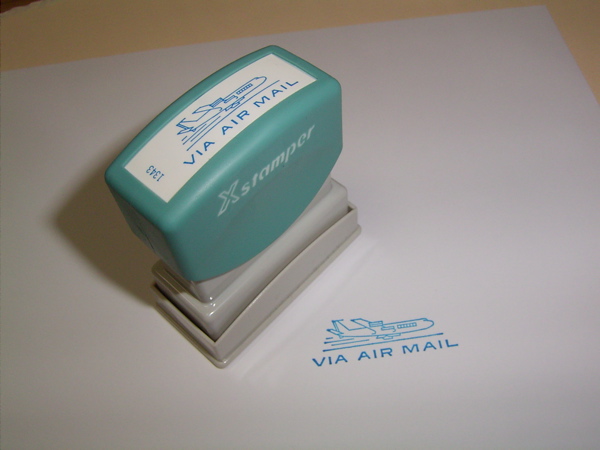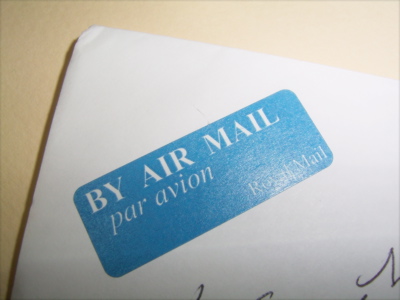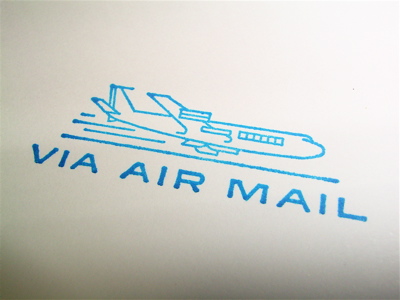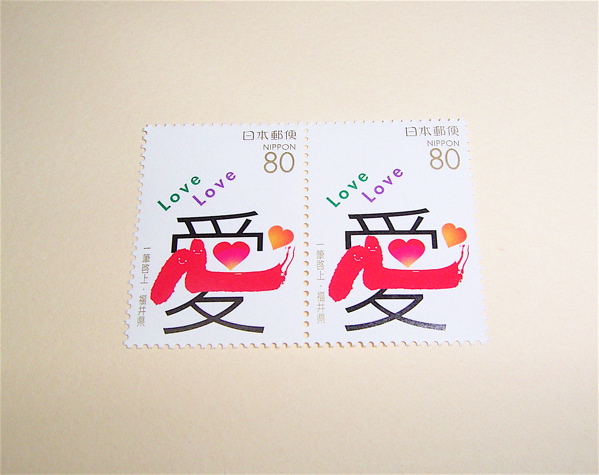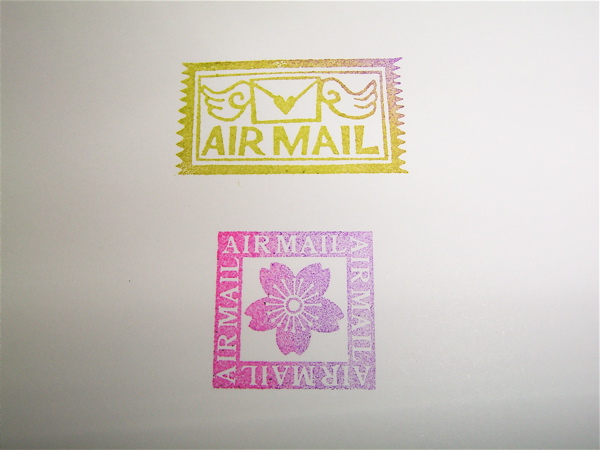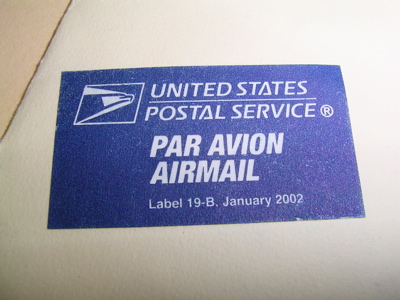
ルーリングペンWS in 神戸 1
週末の土、日は、神戸カリグラフィーフォーラム(KCF)主催の
WSをしてまいりました。
ツールは、ルーリングペンです。あのゴッチャンのではなく、
フツーの烏口を使います。
総勢20名・・・ゼーゼー・・・普段のクラスは6名なのに、3倍以上の
お客様でございます。皆様烏口とお友達になるのは初めての方も多く、「ルーリングペンと仲良くなる」をテーマに進めてまいりました。
烏口のご本業はとにかく「おいらぁ、人生まっすぐさぁ〜」というぐらい、一本気な、否、一本線を
引くことにあります。円を描くにはそれ様のがあるようですし・・・。なので、もちろん曲線には滅法弱いざんす。なので、最初はなだめる様にサンドペーパーで気持ち丸くなって頂きます。
本当に軽〜〜く、軽〜〜く!空気の皮一枚ほど挟んでの作業でございます。(WSのときは、この言葉が出なかった・・・くぅ〜)
上の画像・・・変なサンプルでしょう〜!これは、ルーリングペンの先っちょと腹(横の部分)を使う練習なんです。
これがルーリングペンと仲良くなる基本のように思います。ルーリングペンは固いのであります。
だから、クイルやブロードエッジのように圧を加えればすぐに程よい太さが出るというのではありません!それにみんな手の癖、筆圧・・・様々です。とにかく、先っちょ!腹っちょ!と手がその感覚を覚えていかなくてはなりません。
うはは〜!生徒さん達は、あっという間に想像力豊かな世界を描きながら先っちょ!腹っちょの練習をこなしていきます。
線を描きながらコンポジションも行っていく時、参考にしたのが、アフリカの原住民が作り出す布地でした。
とても幾何学的だったのです。一番上の画像で下側の紙の付箋がついてるのが、
その布地を参考にしたもの。アフリカっていう言葉が頭にあったお嬢さんは、もうアフリカが止まらなかったようで〜キャハハ!シマウマに、ライオンに、ペンギンまで〜。そうかそういう展開もあったかと微笑ましくなりました。楽しみながら慣れるのが一番ですもの!
最初通りかかったときは、途中で
苦戦してるのかしら?と心配でしたが、そんなことはご無用〜!でした。次に見に行ったら、ワォ〜!
いつのまにか凄いことになってます!空間の処理が素敵で、見入ってしまいました!
これも練習のバリエーションで、イニシャルをたくさん作っていくのです。こういう時は、とにかく最初にモノライン(先っちょ)で右方向へ一列にバンバンと少しずつ変化させながら案を出します。
その後は下方向へ腹っちょを使いながら表情を変えていきます。
こうすれば、イニシャルのバリエーションなどあっという間に何十個も出来ちゃいますから〜!!・・・ん?最後の方は、突然変異か・・・?
レイアウト用紙にばかりではつまらないので、キャンソン・ミ・タントのようなラフな色紙に白で書いてみます。
所々にイニシャルデザインも
置きながら練習していき、
どこかに色鉛筆で色をつけて
いっても可愛いです。
練習をしたら、必ず、小作品の
ようなものを作ると励みになりますね。「こんな練習をしていてどうなるの〜」と不安なお嬢さん!
作りましょう〜!
ほら!こうやってレイアウトしながら、線を書き書き・・・。
こんな所にイニシャルをポン!
最後に文章をのせてみてもいいですねぇ〜。
色をつければ、出来上がり!
白く書くには、水彩紙は使用しないので、色鉛筆が
便利です。木炭紙なんかだと相性良いですし!
こんなminimumも練習しましたね。
これも先っちょ、腹っちょの練習で、しかも連続する動きの練習です。
横ばっかりじゃなくてもいいんです!たまには縦にも書きましょう〜。太い線を書くには、ペンは紙面に近くないと出ません。おのずと持ち方に限界が出てくることが理解できます。ルーリングペンは、持ち方も一つではないのです。
でもminimumばかりで・・・この先は?
もちろん!作りましょう〜。
ミニ作品(もどき)で良いのです。
この黒い紙のは、全てminimumだけで構成されています。
いろんなminimumがあるぞ〜!!
こういう練習をたくさんして、
いずれは曲線中心のカーシブへと
発展していくことでしょう〜!
カーシブになると、圧をかける部分が難しいです。
この小作品たちは、minimumも含めて、全て同じルーリングペンで書いています。
先っちょ!腹っちょ!の操作を覚えると同じペンで細い線から太い線まで書けるのです。
さ〜て、次回は20人の妄想カリ人達爆発!?
怒涛のカード作りまでをご紹介致します〜!!みんな凄いんだぁ〜!
彼女のパレット
mojitor-sさんのワークショップ楽しそうですね!素敵な色が勢ぞろいでうっとりしました。
綴じ糸にマルッコちゃんつけるの、いいでしょ?ドットにぴったりですね。
さて、先日のこと。
「sさんのパレットが欲しいわ〜」と言いながら、ブックのページ作りの作業をするためにご自分のパレットを取り出したKyokoさんです。
おやおや、なーに?透明なフタに番号がふってある仕切りのついたパレットです。深さがありますね。
伺ってみると、透明水彩絵の具にご自分で番号をつけ、その番号に対応させたオリジナルのパレット。筆に水をふくませたら、すぐ始められます。
なるほど〜、これはどの色を出したんだっけ?とすぐ忘れてしまいますもんね。
簡単なように見えて、これは優れものです。このケース、実は薬入れなのだそうですよ。7日×4週間で1か月分の薬を入れられるもの。
一つ一つにフタ(錠剤が落ちないように、でしょうか)がついていたそうですが、それをカットしています。
この薬入れのアイディアはもとはお友達から伝授されたそうですが
絵の具に番号をつけたところがKyokoさんオリジナルですね。
こういう薬を入れるケースは、1週間用とか2週間用はよくあるそうなのですが、このような1か月分を入れられるたくさん仕切りのあるタイプは、あちこち探しても見当たらないとか。
彼女とワークショップなどで同じテーブルになった人はわかると思いますが、
とにかく作業が手早いのです。それにはこういう日頃の準備もあったのですねえ。
見習わなきゃ!
と、見ている間にさっさと作業を始めちゃったんですね〜。
少しずつ色を混ぜながら、美しい色が筆からあふれてきたのでした。
ドットそしてまたドット
ドット、ドットのワークショップが終わりました。まるで草間弥生の様。ドットばかりの一日でした。
この色とこの色を合わせると、あらま、こんな色が〜!!
思ってもみない色が出現して、大発見もありますね。
所狭しとパレットが広げられ、頭を整理しながら、格闘しました。
これが本当にひと苦労。色味や鮮やかさに惑わされると、わからなくなってしまいます。
一見明るく見えても、実は以外と暗かったり。ふ〜〜む、難しい。
それをノートに仕立てたページに貼って出来上がり。
一日が終わる夕方には、皆疲労困憊。今日はお昼休みが10分しかなかった〜という方もいて、そうでしょそうでしょ、お疲れですよね。
本当にご苦労さまでした。まだ出来上がっていない人もいたのでこれで全部ではありませんが、それぞれ苦労のかいがあって、とても素晴らしいサンプルブックが出来ました。
今回、本当に疲れちゃったと思いますが、基本色に白黒グレーだけじゃなくて、適当な色を混ぜて仲良しこよしの色をたくさん作ってみましょうね!!
優しさに包まれたなら〜。
私が物欲しそう〜〜〜(かなり)に、mojitor-sさんの
紹介していたペットボトルカバーについて語っていた
ところ・・・カタコン・・・。
ぉお〜幸せの音が・・・カタコン。
その前に・・・バリッバリッ・・・封筒のテープをはがし・・・。
な、な、なんだ!もしかしたら包み紙が・・・手書き?
sさんが洋服を買うあのお店?の包み紙・・・かどうかは
わかりませんが、あのクシュクシュする柔かい紙に
このレイアウト!色鉛筆でビルトアップなカラフルな文字が
いますよ!いますよ!
キャホホ。
こんな贅沢なことでいいのでしょうか?!
そして中身はもちろんあのあったかになるために で
登場したカバーですぅ〜。
ウフフ。ウフフ。
優しさに包まれた気持ちってこういうのを言うんでしょうね。
「ご、ご主人さま・・・。私、とてもヌクヌクでございます。
優しい気持ちとは、このようにフワフワになるので
ございますね・・・。」
ポッチンや、それはペットカバーじゃなくて、
ボトルのカバーざんす!
バックダンサー付き製本はいかが?
週末は、神戸でルーリングペンのWSをしました。寒い中、大勢の方に参加して頂き、
20名の妄想カリ人(勝手にすみません)のすごい発想力に、私も大変刺激を受けた
次第です。WSの様子はまた後日にご紹介いたしますね。ウフフ。
If'n Books demonstration video
WSは受ける方、与える方と、どちらの立場にいても思うことが、「動き」です。
何かをしようとしていて、よく解らなくてどうしようもない時ってありますよね・・・。
(だいたいいつもか・・・)
本の写真を見てわかるときもありますが、実際のところを見られたらどんなに良いだろうか・・・。
今や、動画の時代!探せばあるもんです!
You Tubeで製本についてもたくさん動画があるようです。アクセス数が多い人気のものが
上の画像です。
ちゃんと製本している後でたくさんのダンサーが踊る・・・躍る・・・?「何で?」
クレジットには「her dancers」とかなってますよ・・・!「へっ?」
それは彼女のお友達、ファン、親衛隊なのか・・・それとも彼女の頭の中の人達が
躍ってくれるのか・・・!「ほぉ〜?」
どちらにせよ、製本中の道具は必見!綴じ台が欲しい〜!糊の後にローラーみたいの
かけてるし・・・。
でもついついダンサーに見とれて・・・気付いたら製本終了してます(爆笑)!
動画は助け舟の一つ!それでもWSやクラスに参加するのは、やっぱり「聞いて!」
コミュニケーションが一番大切なんだと思うわけです。
こんなところでお役立ち
今日はワタクシ、お歌の発表会でございます。
久しぶりにミシンを出して衣装(?)のロングスカートも縫いました。学芸会の準備みたいです。
Par Avion
いつも海外へ手紙を出すときは、この航空便用のシールを貼っています。ちゃんと運んでもらえそう、と淡い期待を抱いています。
アメリカやイギリスのはこんな感じです。どこも青に白文字というのはどうしてでしょう。交通標識と同じで、一番目につきやすくはっきりと読めるからでしょうか。
あら、確かにこれも青ですね!
さて、こちらはair mailのゴムのスタンプ。
桜のAirMailスタンプは、いかにも日本からのお便り、という雰囲気でいいけれど、これを郵便屋さんがちゃんと航空便だと認識してくれるでしょうかね〜
。青でスタンプすれば大丈夫なのかもしれませんね!?
さてさて、バレンタインデーの時にお見せしようと思っていて忘れていた切手をご紹介します。
この切手!愛の切手です。
心の点々がハートになってますよ〜
これは福井県で発売されたものだそうです。ひゃ〜、こんな切手でラブレターが来たらどうでしょう。
うう〜ん・・。
嬉しいけど、直球すぎてちょっと引く・・かも・・?!